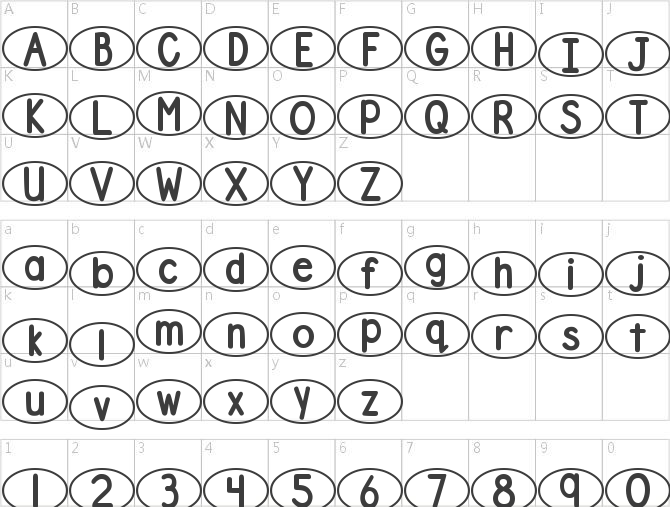
DJB Standardized Test Oval 2
DJB Standardized Test Oval 2介紹
DJB Standardized Test Oval 2字體字庫是一款讓人賞心悅目、百看不厭的英文字體,適合各類廣告和產品包裝設計應用,字體大小0.02MB,格式為ttf字體,上傳用戶是dqq520,作者/版權方為未知